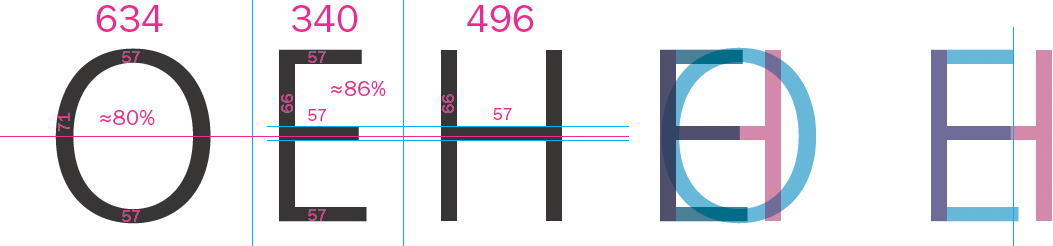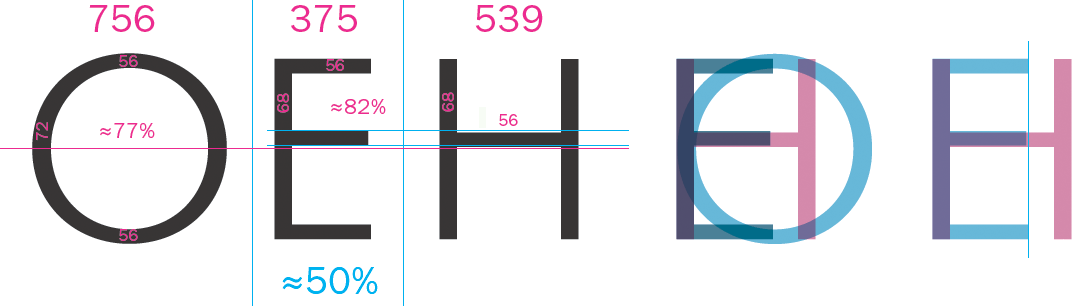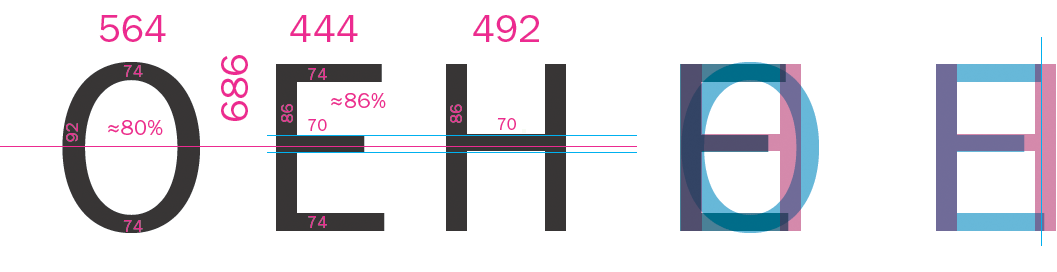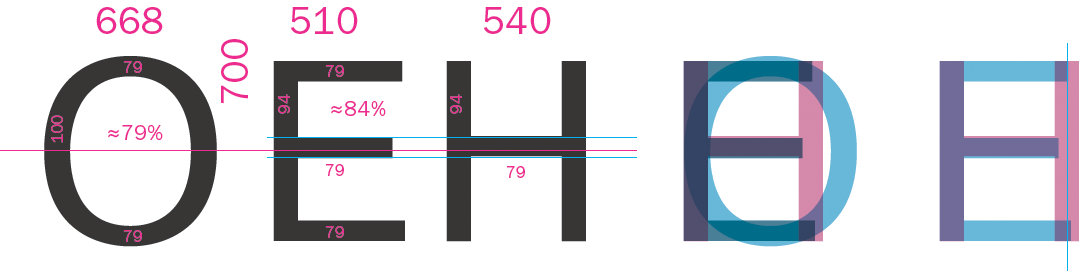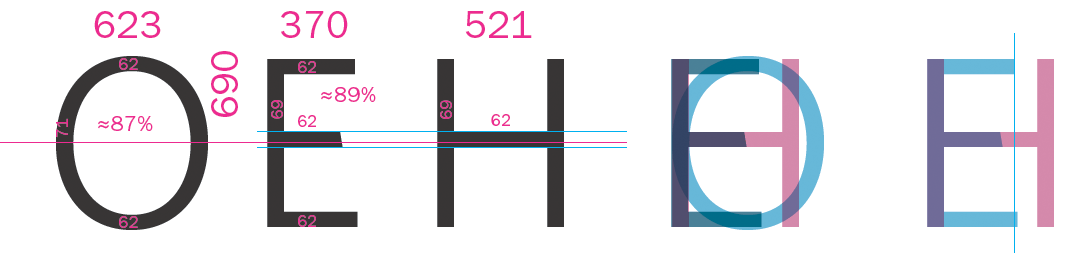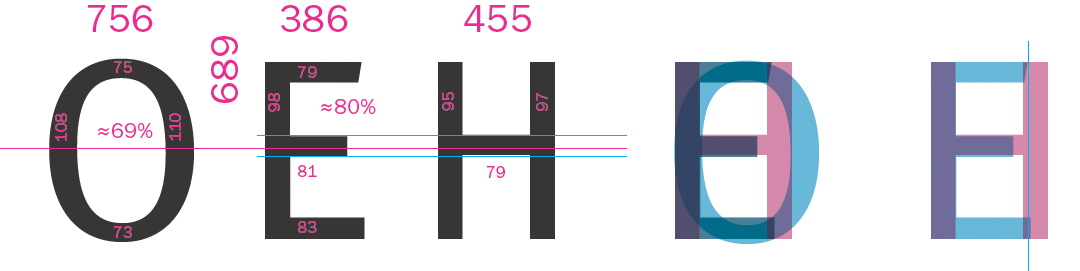
Sans proportions |
Пропорции в гротесках по трем основным прописным знакамОтмечаются отношения горизонтального и вертикального штриха, отношения высоты и ширны знака, ширина знаков относительно друг друга. Frutiger (FreeSet)![]() Futura (Futuris)![]() ITC Franklin Gothic![]() Helvetica (Pragmatica)![]() Whitney![]() FF Meta![]() |